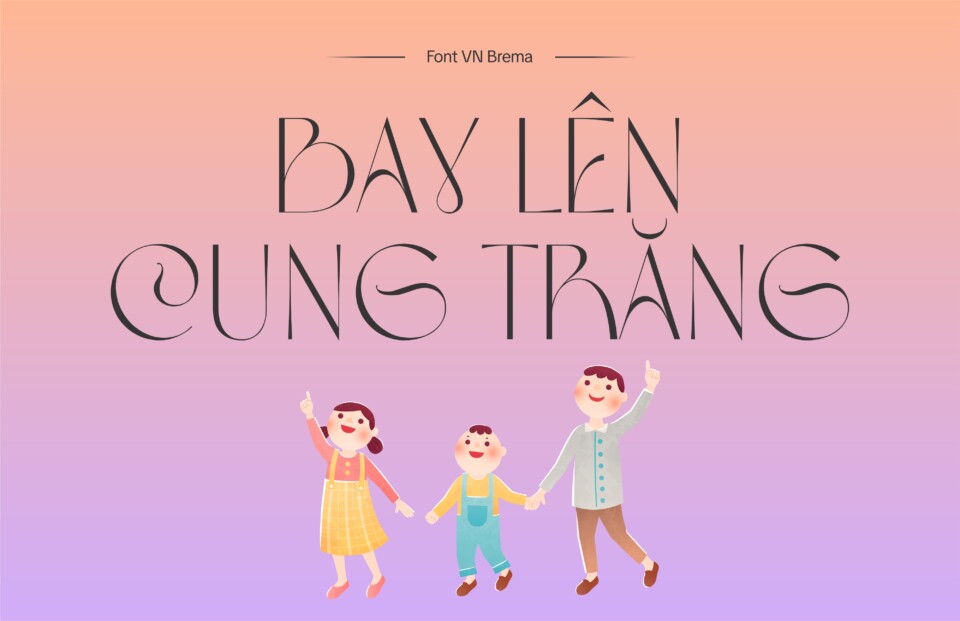
Font Việt hóa VN Brema
Giới thiệu về Font Việt hóa VN Brema trong thiết kế đồ họa
Trong thế giới thiết kế hiện đại, việc lựa chọn một bộ Font Miễn Phí chất lượng luôn là ưu tiên hàng đầu của các bạn học sinh và giáo viên. Font Việt hóa VN Brema nổi lên như một giải pháp hoàn hảo cho những ai đang tìm kiếm sự kết hợp giữa nét cổ điển và tính ứng dụng cao. Đây là bộ phông chữ được tinh chỉnh kỹ lưỡng để phù hợp với bảng mã tiếng Việt, giúp loại bỏ hoàn toàn các lỗi hiển thị dấu phổ biến. Với cấu trúc đường nét thanh thoát nhưng không kém phần mạnh mẽ, bộ font này mang lại cảm giác chuyên nghiệp và chỉn chu cho mọi bản thảo. Việc sử dụng Font Việt hóa VN Brema không chỉ giúp nội dung trở nên dễ đọc hơn mà còn tăng thêm giá trị thẩm mỹ cho các sản phẩm trình chiếu tại trường học. Đối với cộng đồng thiết kế tại Việt Nam, đây là một công cụ đắc lực giúp hiện thực hóa các ý tưởng sáng tạo một cách nhanh chóng và hiệu quả nhất.
Đặc điểm nổi bật của bộ Font Việt hóa VN Brema
Thiết kế tối ưu và độ tương thích cao
Font Việt hóa VN Brema sở hữu những đặc điểm nhận dạng độc đáo với các đường bo góc mềm mại nhưng vẫn giữ được khung xương vững chãi. Điểm mạnh lớn nhất của bộ font này chính là sự đa dạng trong các biến thể từ chữ gầy (Thin) đến chữ đậm (Bold), cho phép người dùng linh hoạt áp dụng vào nhiều vị trí khác nhau trong văn bản. Khi trình bày các bài thuyết trình hay thiết kế báo tường, Font Việt hóa VN Brema giúp tạo ra sự phân cấp thông tin rõ ràng giữa tiêu đề và nội dung chính. Hơn nữa, font chữ này còn được tối ưu hóa để hiển thị sắc nét trên cả màn hình máy tính lẫn khi in ra giấy, đảm bảo tính nhất quán cho toàn bộ dự án của bạn.
Ứng dụng thực tiễn trong học tập và giảng dạy
Không chỉ giới hạn trong lĩnh vực nghệ thuật, Font Việt hóa VN Brema còn được ứng dụng rộng rãi trong môi trường giáo dục. Các giáo viên có thể sử dụng bộ chữ này để thiết kế bài giảng điện tử sinh động, thu hút sự chú ý của học sinh. Đối với các bạn học sinh, việc dùng Font Việt hóa VN Brema cho các bìa báo cáo hay tiểu luận sẽ tạo nên một ấn tượng tốt về sự nghiêm túc và sáng tạo. Sự gần gũi và dễ nhìn của bộ font này giúp giảm bớt sự căng thẳng khi phải tiếp nhận một lượng lớn thông tin chữ viết, từ đó nâng cao hiệu quả truyền đạt kiến thức trong nhà trường.
Kết luận về giá trị của Font Việt hóa VN Brema
Tổng kết lại, Font Việt hóa VN Brema là một lựa chọn tuyệt vời dành cho những ai yêu thích sự tinh tế và tính đa dụng trong thiết kế. Với khả năng hỗ trợ tiếng Việt hoàn hảo và phong cách thẩm mỹ hiện đại, bộ font này chắc chắn sẽ là người bạn đồng hành tin cậy trong các hoạt động học tập cũng như làm việc hàng ngày. Hãy trải nghiệm ngay sự khác biệt mà phông chữ này mang lại để nâng tầm các sản phẩm sáng tạo của chính mình. Đừng quên truy cập vào Font Miễn Phí, Font Việt Hóa, Font Việt hóa VN Brema để khám phá thêm nhiều tài nguyên hữu ích khác phục vụ cho niềm đam mê thiết kế của bạn.